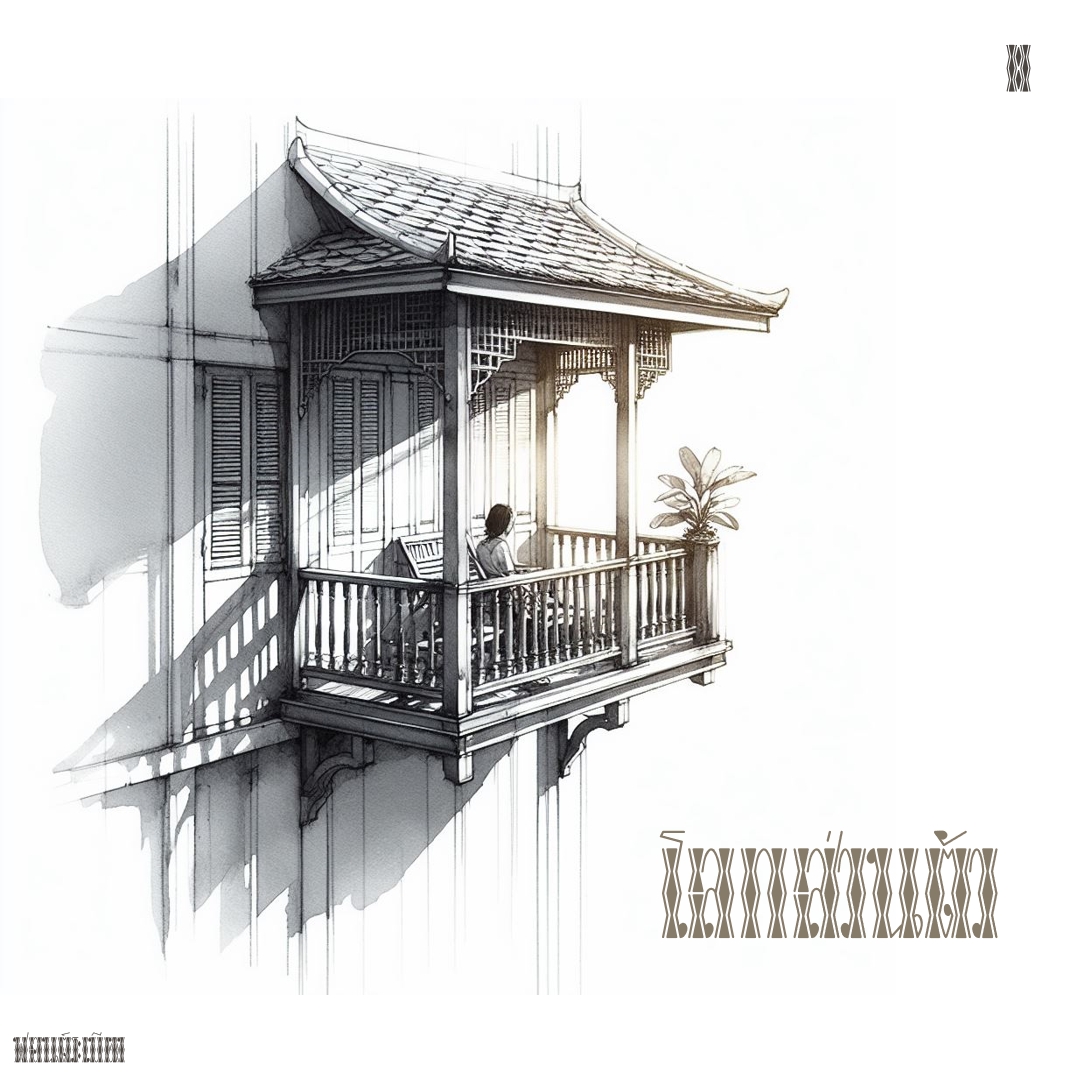
ฟอนต์ ระเบียง
ฟอนต์ระเบียง เรียงเป็นแถว เอาไว้ตกแต่ง จะอ่านต้องหยีตา..จึงพอเห็น ใช้เป็นพาดหัวยังยาก ข้อความอย่าได้ทำ :)
ชื่อฟอนต์ : ระเบียง
ฟอนต์ระเบียง เรียงเป็นแถว เอาไว้ตกแต่ง จะอ่านต้องหยีตา..จึงพอเห็น ใช้เป็นพาดหัวยังยาก ข้อความอย่าได้ทำ :)
:3005: สวยครับแต่ทรมาน
โหดๆ แปลกๆ เห็นปุ๊บก็รู้เลยฟอนต์ใคร 99.99%  :45: